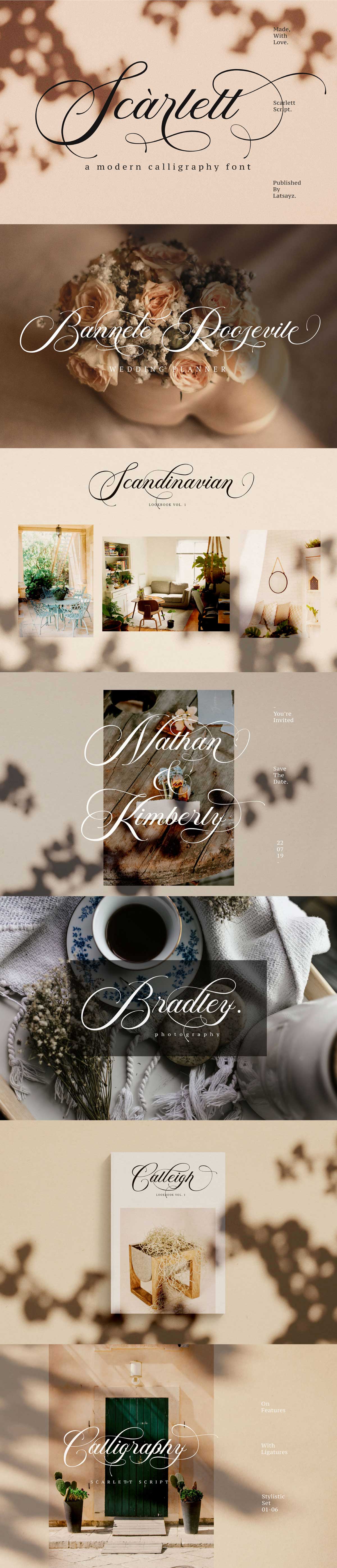
女性向けの媒体やアパレルなど、幅広いジャンルのデザインに大活躍間違いなしです。
「The Luxury Font Bundle」の気になる中身
今回のバンドルの中で、私が特に気になるフォントはこちらです。
Sunflora
連字のデザインがユニークなSunflora。さりげなく目をひく見出しやロゴがこのフォントだけで簡単に作成できます。
Mance Rose
Mance Roseはスクリプトとセリフフォントのセットです。それぞれ単体で使ってもいいですが、ペアで使うとよりデザインが華やかになります。花柄の素材もついてきますよ。
Scarlett
Scarlettは今っぽいカリグラフィフォント。リガチャを使いこなせば、美しい招待状やポスターのデザインも短時間で出来上がりです。
Gerhard
クラシックな雰囲気が漂う多言語対応フォントGerhard。落ち着いた雰囲気の媒体にぴったりで、ひとつあると何かと便利な書体です。
Rolves
ウェイト4種&イタリック体で合計8フォントが収録された「Rolves」。シンプルで使いやすく、遠くからでも読みやすい書体です。
Coachella
6種類のウェイトが揃ったCoachella。どのウェイトも読みやすく、特に細いウェイトは小さくても読みやすいのが嬉しいですね。流行りのセリフフォントが欲しいなら、お買い得な今がチャンスです。